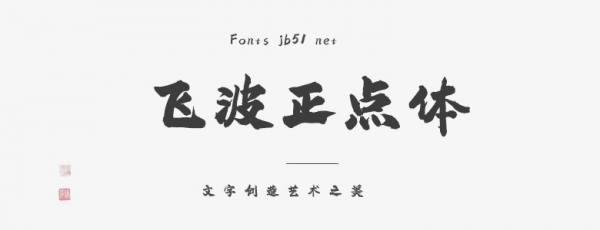
飛波正點體由本人從毛筆手寫到后期軟件封裝,創(chuàng)作歷時一年時間,完成共7千多字。初次制作字庫,經(jīng)驗不足之處,歡迎指正。
字體風格穩(wěn)重,氣勢上揚,筆畫厚重有力是此套字庫的特點。適用于各種標題大字排版,電影海報、包裝、電商、品牌名稱、漫畫、影視綜藝、游戲、各類商業(yè)海報、戶外廣告標題等。